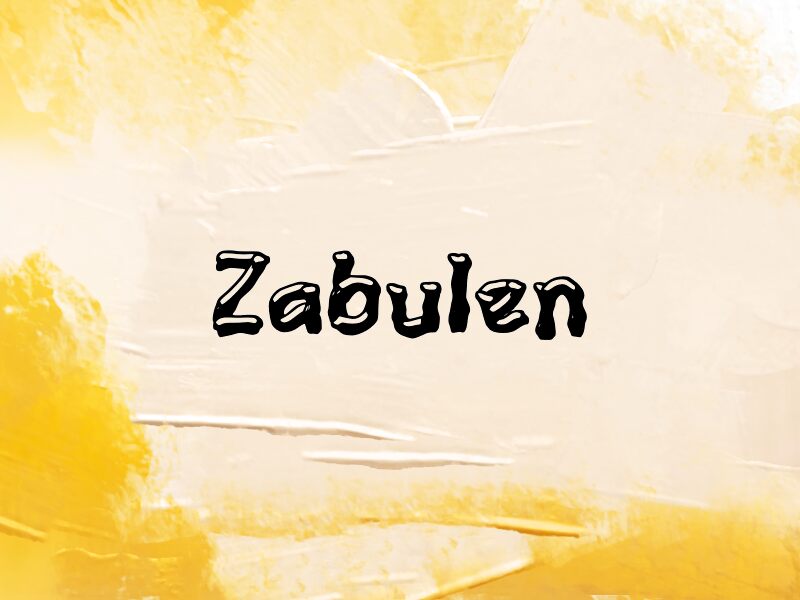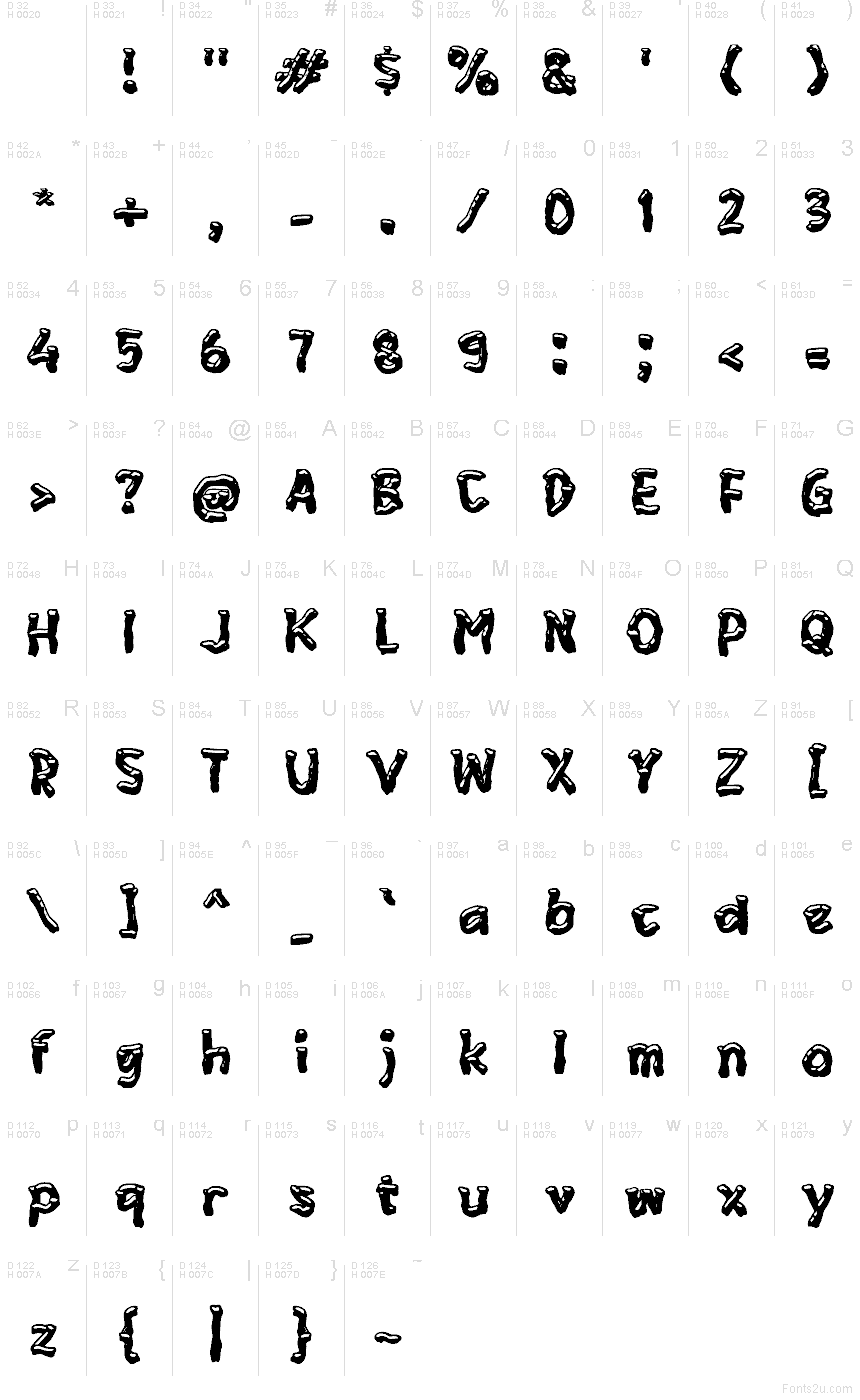
Zabulen
Zabulen от Wep - это бесплатный акцидентный шрифт в мультяшном стиле. Его силуэты напоминают раздутые кляксы чернил, из-за чего кажется, что буквы были буквально налиты, а не нарисованы. Неровные края и яркие внутренние вырезы придают этой массивной черной форме живость, создавая эффект «резинового» комиксного шрифта, а не просто декоративного оформления.
Этот дерзкий, «надутый» ритм отлично смотрится на детских плакатах, обложках комиксов, названиях игр, упаковках снеков и превью для YouTube, где короткие слова должны играть роль броского графического элемента. Шрифт также подойдет для приглашений на вечеринки или мерча, так как его «кляксообразные» формы считываются скорее как нарисованные от руки звуковые эффекты, чем как стандартные буквы.